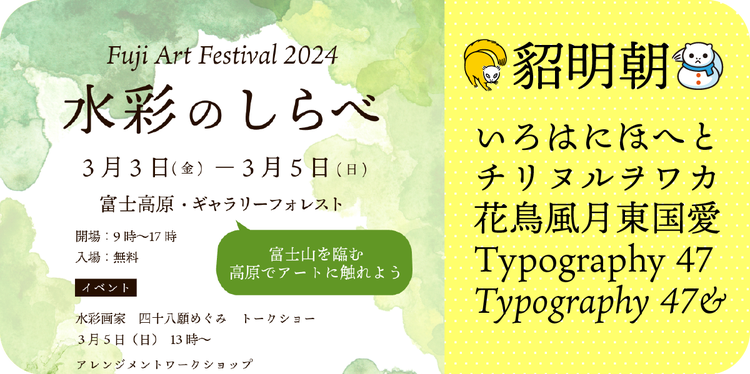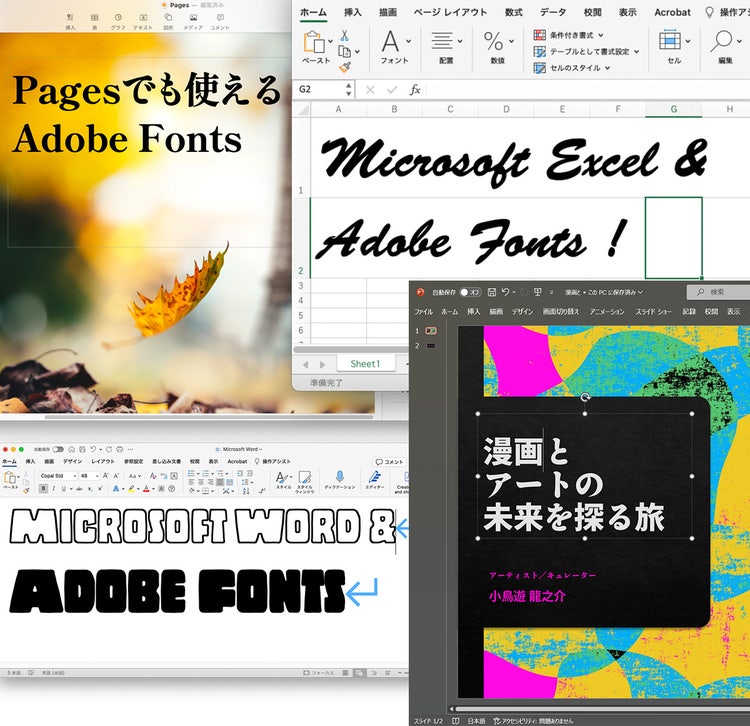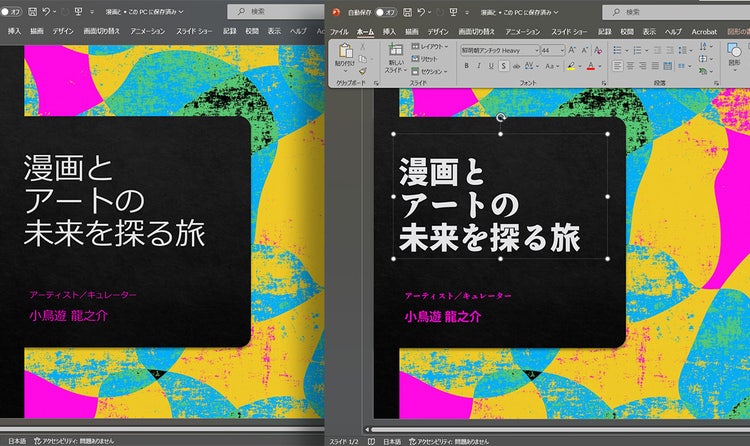
Adobe Express+Adobe Fontsで
「デザインにチャレンジしたいけれど自信がない」「プロのツールはまだちょっと敷居が高く感じる」そう思い悩む人に、ぜひオススメしたいのが、無料で使えるアドビのコンテンツ制作アプリ「Adobe Express」です。
目的や用途に合わせたテンプレートを選び、文字や写真を入れ替えていくだけで、プロさながらのデザインを作り上げることができます。デザインに挑戦したい、自分らしいグラフィックを作ってみたい……そう思ったら、Adobe Expressを開いてみましょう。
Adobe Expressは、プロ向けのフォントが多数揃う、Adobe Fontsともスムーズに連携しているため、文字のデザインバリエーションも非常に多彩です。
この記事では、Adobe Expressで使ったフォントを、自身のパソコンに入っているほかのアプリケーションでも使う方法について解説します。
アドビ以外のアプリでも使える無料フォントが2,000以上
アドビが展開する「Adobe Fonts」は、日本語、英語だけでなく、中国語簡体字・繁体字、韓国語から世界のさまざまな文字・言語に対応したクラウドフォントサービス。Adobe Creative Cloudに契約しているユーザーなら、25,000を超える高品質なフォントを自由に使うことができます。
“Adobe” Fontsという名前から、「アドビアプリでしか使えないんじゃないの?」「有料プランに契約している人向けのサービスでは?」と思っている人も多いのではないでしょうか。Adobe Fontsには、有料プランの契約がなくても使えるフォントが2,000以上も用意されています。Adobe IDさえあれば、追加料金なく、アドビアプリ以外でも自由に使うことができます。
フォントが多い=表現力が広がる&デザインも魅力的に!
「いろいろなフォントが使えるとどんなメリットがあるの?」そう考える人もいるでしょう。いまのパソコンには高品質なフォントが多数搭載されていますが、それでも、自分が作りたいものに100%マッチするものが入っているとは限りません。
デザインにおいて、文字は「読めればいい」ものではなく、「どう伝えたいのか」をプラスしたほうがより強いメッセージになります。また、普段作っているデザインも、文字を見慣れているフォントから変えてみるだけで、より多くの目に留まるものに仕上げることもできるでしょう。そのときに役立つのがフォントです。フォントが多く使えるということは、文字の表現力を大きく広げることになります。
上はプレゼンテーションの文字をOS標準のフォント(左)から、Adobe Fontsで提供されている「貂明朝アンチック」に変更(右)したものです。
フォントが変わるだけで、伝わる雰囲気も大きく変わることがわかります。
これは Adobe Express のテンプレートを使い、貂明朝を使ったデザイン例です。デザインの現場でも人気の「貂明朝 Regular/Italic」も無料で使えるフォントのひとつ。
Adobe Expressで使いたいフォントを探すときにも便利なAdobe Fonts
Adobe Expressで使えるフォントとAdobe Fontsで使えるフォントはまったく同一です。そのため、Adobe Expressで使うフォントを効率的に探すためにも、Adobe Fontsは役立ちます。
Adobe Fontsでは言語やフォントの種類(明朝体・ゴシック体など)から検索できるほか、サンプルテキストを自分で指定することもできるので、イメージに合うフォントを素早く見つけることができるでしょう。
「デザインって楽しい!」「フォントっておもしろい!」そう感じたら、Adobe Expressだけでなく、Adobe Fontsにも触れてみましょう。多彩なデザインを持つ、無数のフォントに出会えるはずです。